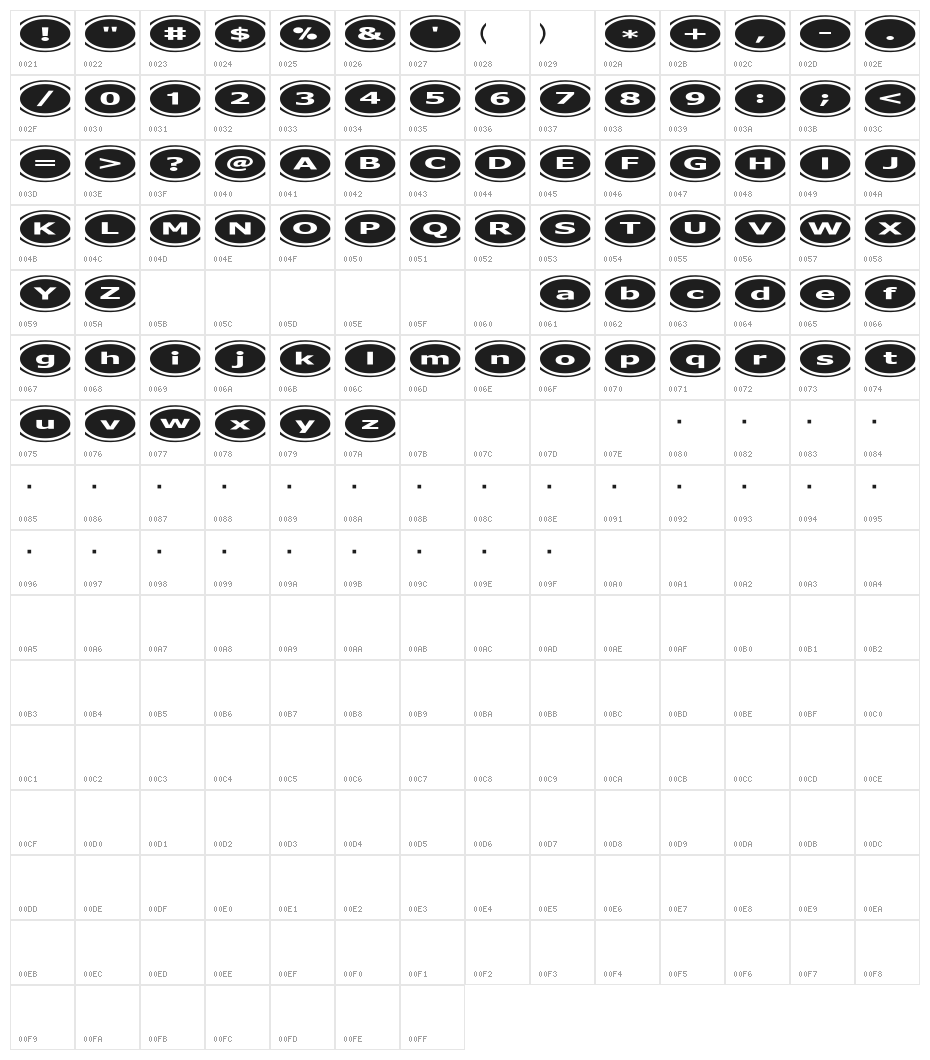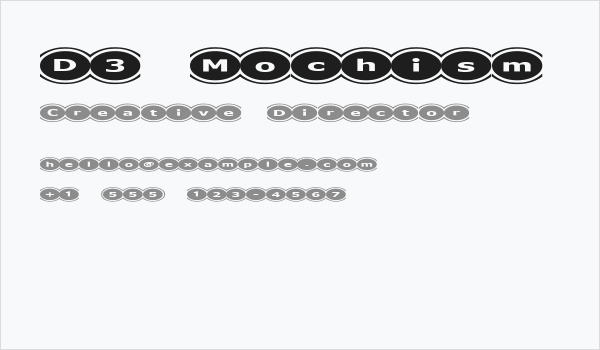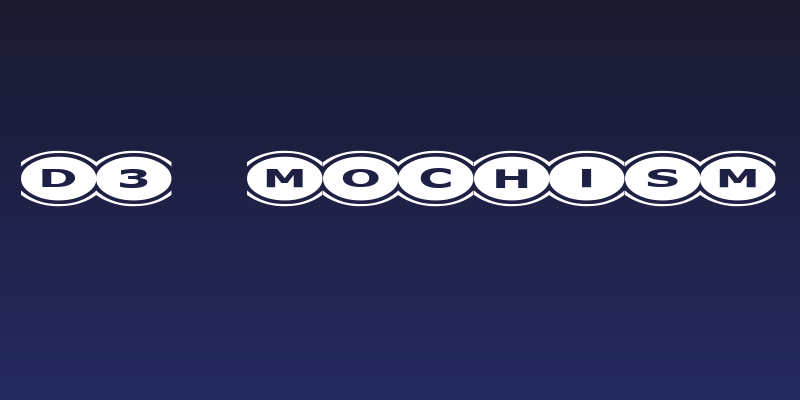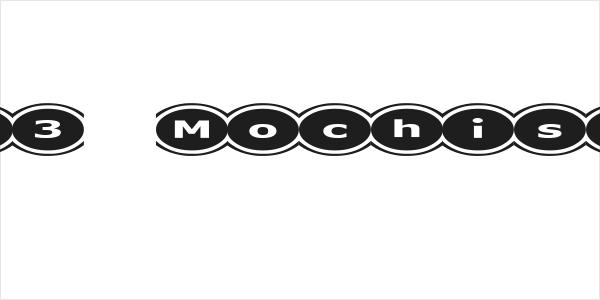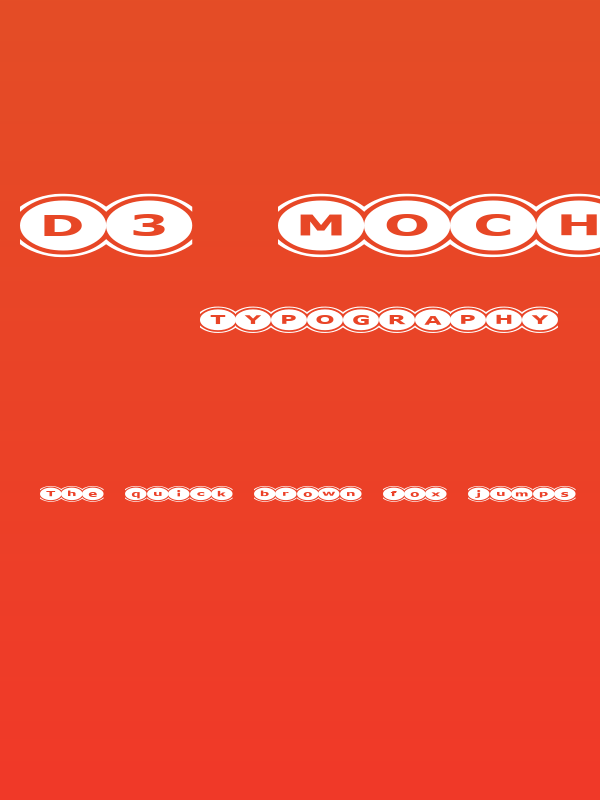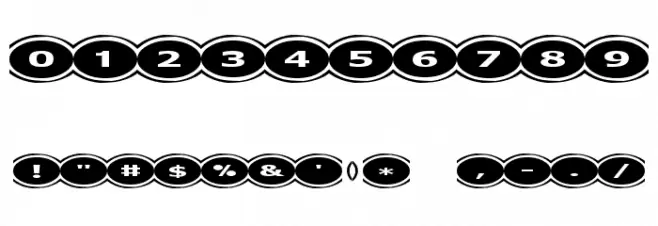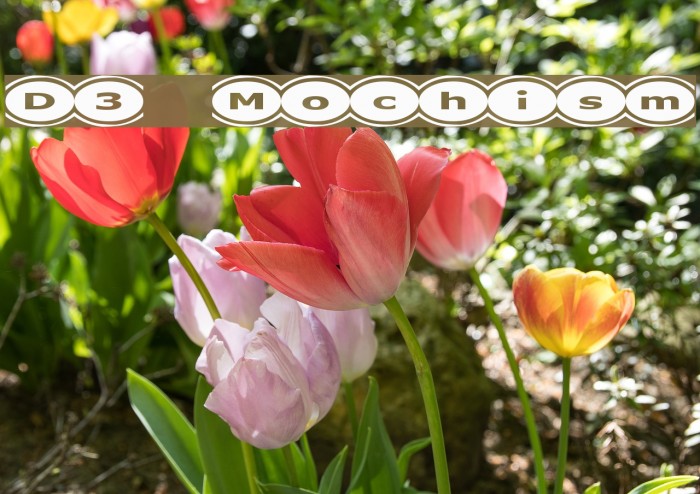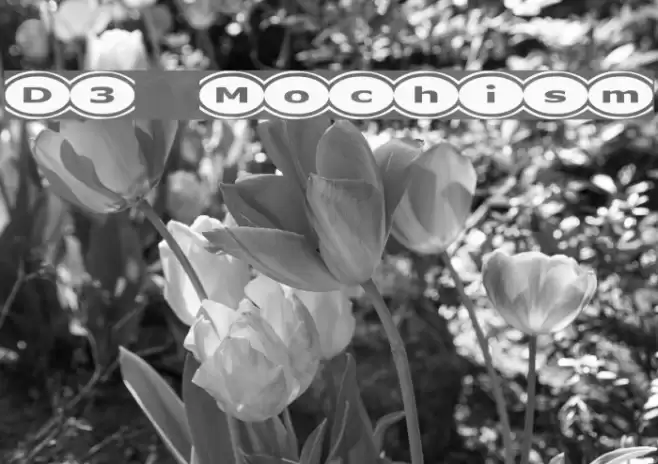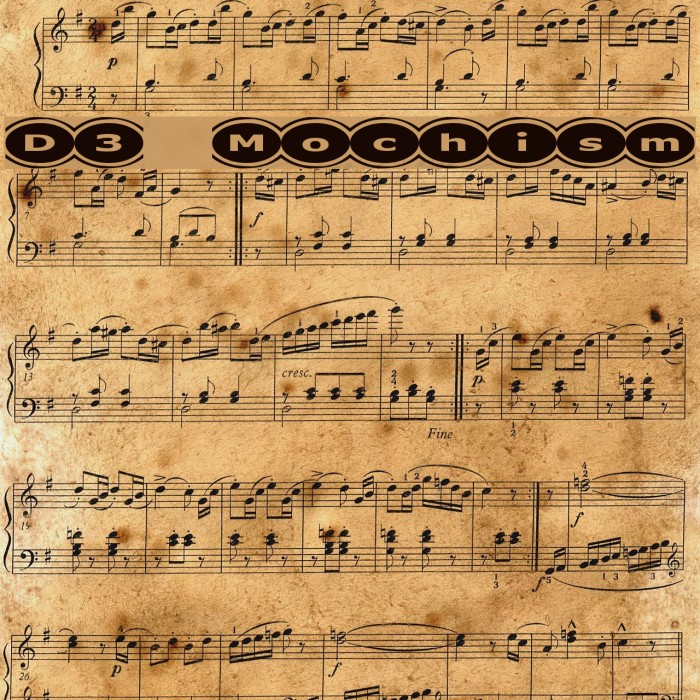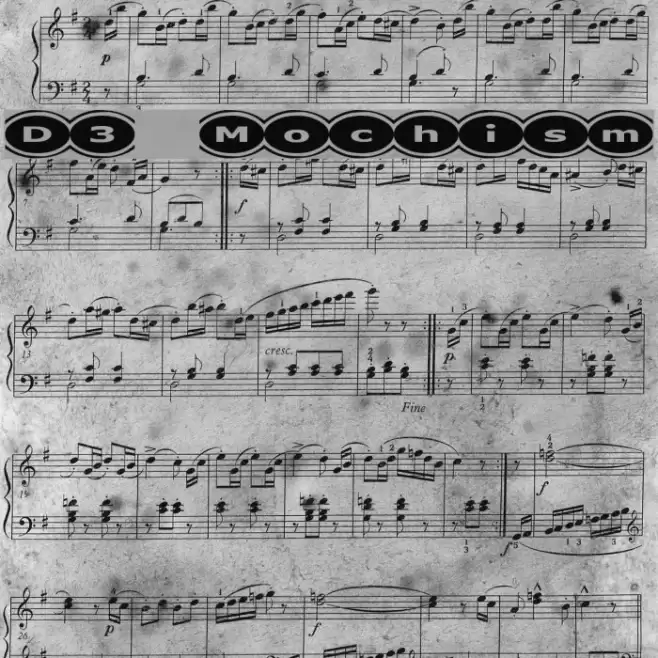
D3 Mochism Font
| Stil general | Modern, Decorative |
| Caz de utilizare | Logos, Posters, Branding |
| Proiecte propuse | Ideal for logos, posters, and branding materials that require a bold and playful aesthetic. |